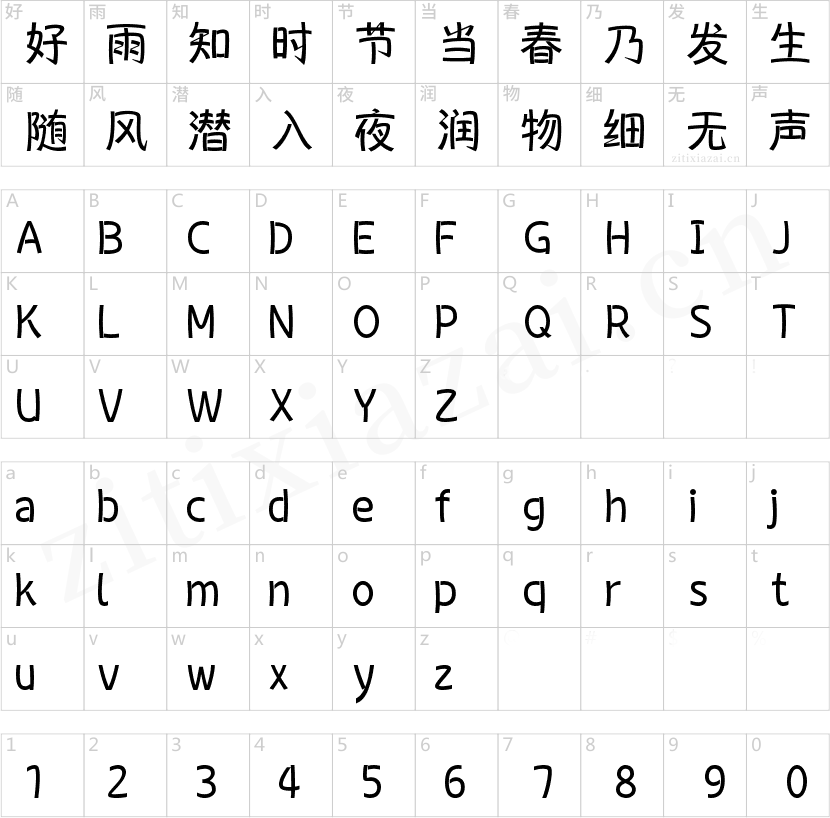
字魂舞丝线体
字魂字体字魂舞丝线体字体是由字魂创意字库设计并生产的一款可商用的字体,被收录于字魂先锋系列。该字体支持GB-2312标准以及最新的字魂ZH7144标准,包含7144个中文、字母、符号和数字,字体类型偏向创意字体,具有活泼、可爱、简约的风格,在市面上广泛用于印刷品&包装、化妆美容、媒体&H5等场景。